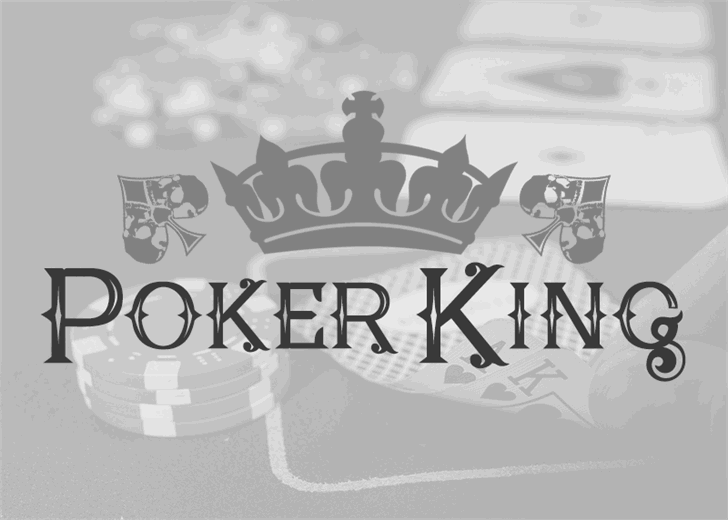
Na categoria de fonts gothicas, apresentamos a Poker Kings font, criada pelo designer Hamilton. Essa fonte é perfeita para aqueles que buscam uma aparição elegante e minimalista no design de sites ou materiais gráficos. Com um estilo poderoso e distinto, a Poker Kings se destaca em qualquer projeto onde deseja transmitir confiabilidade e autoridade visual. Com seu uso elegante do tipo gothic, você pode destacar sua marca com um design arquitetônico que expressa robustez e simplicidade. Ideal para círculos profissionais como fins de negócios ou administração pessoal, a Poker Kings oferece uma opção perfeita para quem busca transmitir um estilismo sóbrio e imponente. Seja para uso em materiais impressos ou digital, ela será uma escolha inteligente que reforça sua marca com estilo.